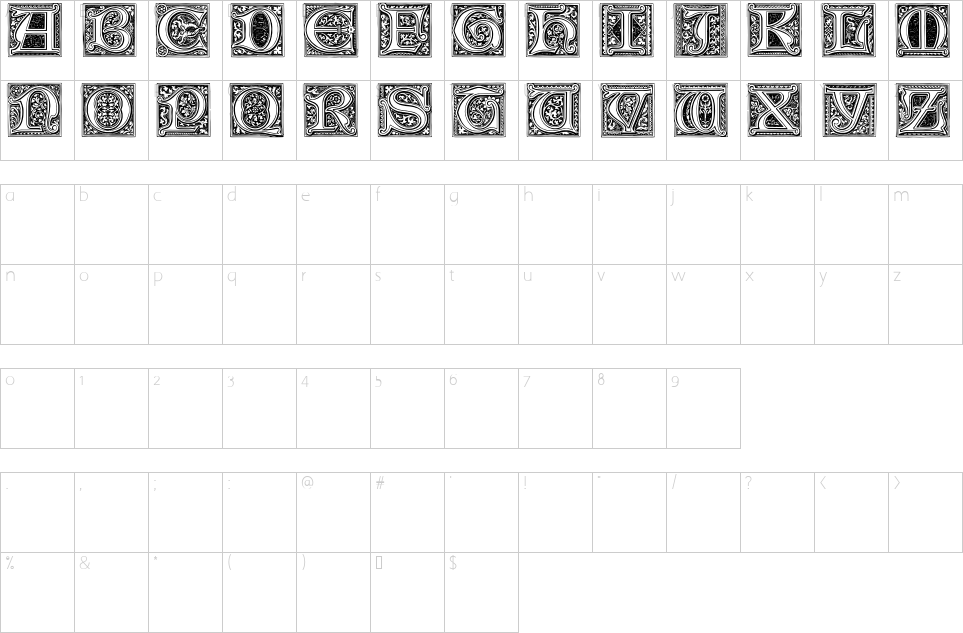
A Medieval Victoriana é uma fonte elegante e sofisticada, criada por Paul Lloyd, disponível gratuitamente tanto para Windows quanto para Mac. Essa fonte medieval-vitoriana traz uma mistura única e atraente de estilos, combinando elementos do gótico medieval com um toque de modernidade vitoriana. Sua gradação de caracteres cuidadosamente elaborada e sua disposição harmônica fazem dela uma escolha ótima para design gráfico e publicidade. Convidamos você a experimentar essa fonte exclusiva e única, que é perfeita para criar designs memoráveis e elegantes. Desde o design de websites até o layout de livros, a Medieval Victoriana oferece uma paleta de opções que ajudará a tornar suas criações ainda mais notáveis.